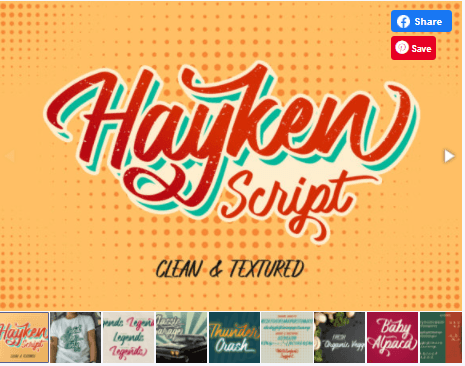
Hayken Script Font
Hayken - это скриптовый шрифт с динамичным и энергичным стилем. Его можно использовать для различных целей, таких как заголовки, логотипы, футболки, фирменные бланки, вывески, этикетки, информационные бюллетени, плакаты, значки и любой другой дизайн, для которого требуется уникальный и яркий шрифт. Добавьте его к своим самым креативным идеям и обратите внимание, как они оживают! Этот шрифт имеет кодировку PUA, что означает, что вы можете легко получить доступ ко всем глифам и росчеркам!